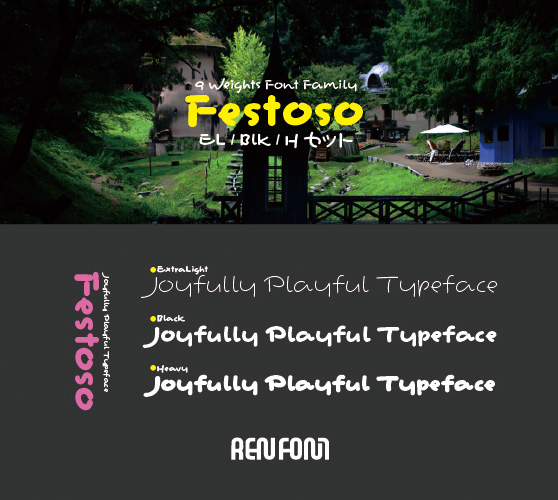
欧文手書き
Festoso-タイトル・大見出し用3ウェイトセット(EL/Blk/H)
Festoso-ExtraLight,Festoso-Black,Festoso-Heavy
破天荒でバラエティに富んだ多言語欧文
“Festoso” は「ほんまるかな」の従属欧文として制作されたため、そのデザインには当然ながら「ほんまるかな」の持つ特徴が反映されています。
当社タイプデザイナー金井和夫の普段使いの文字をベースとしてデザインされ、わずかに筆文字の痕跡を残した、一風変わった丸文字的フォルムイメージを持っています。
Festoso はイタリア語の音楽用語で、「陽気な」「楽しい」といった意味があります。音楽においては、演奏を陽気に、お祭りのように明るく行うよう指示する際に使われる表現です。この書体 Festoso も、まさにそのお祭りのような陽気さを表現しています。跳ねる文字もあれば、ピタッと止まる文字もあり、予測不可能でバラエティに富んだ、リズム感あふれる破天荒なデザインです。使っているだけで気分が高まり、無条件に楽しくなってくるフォントです。タイトル・大見出し用3ウェイトセット。